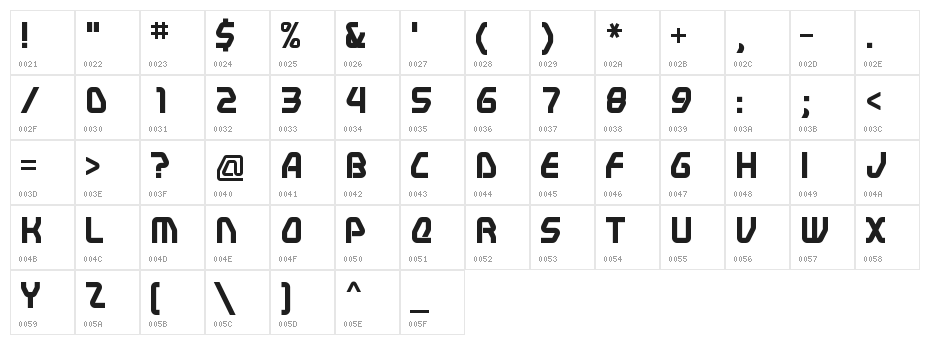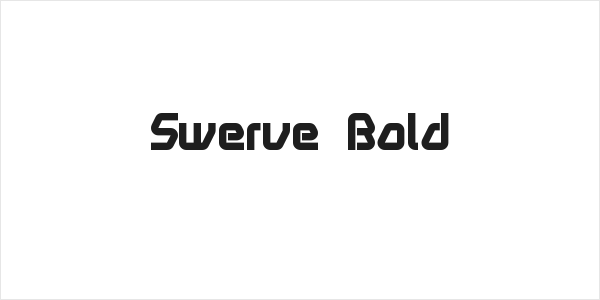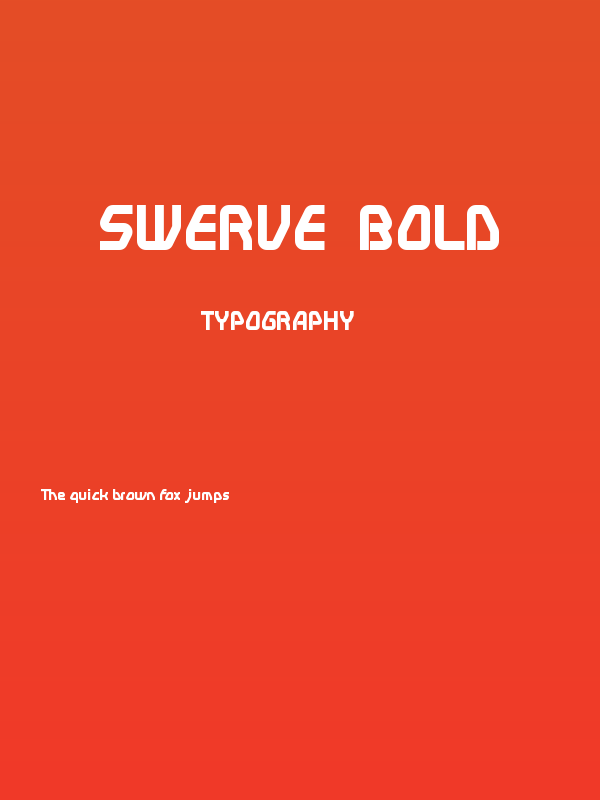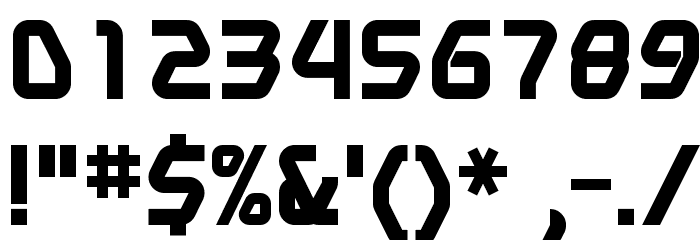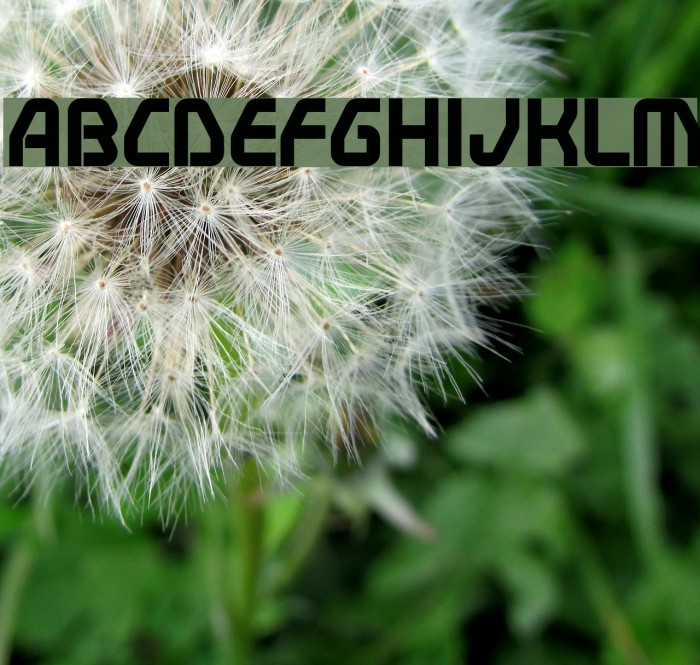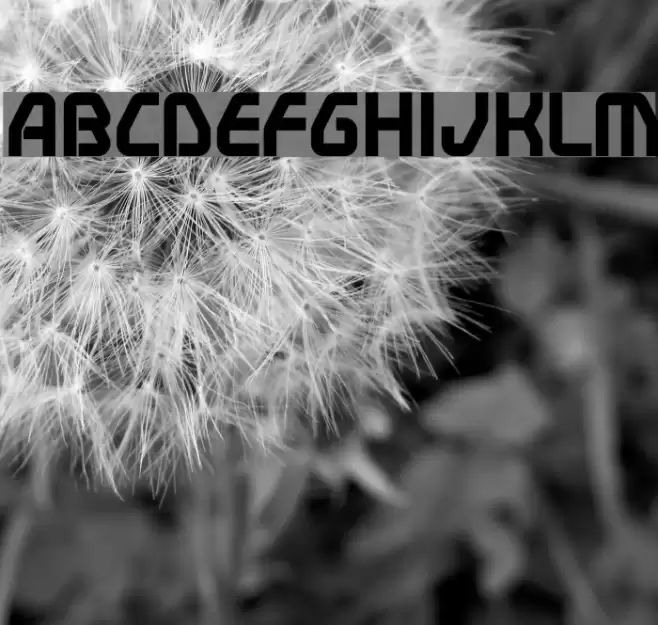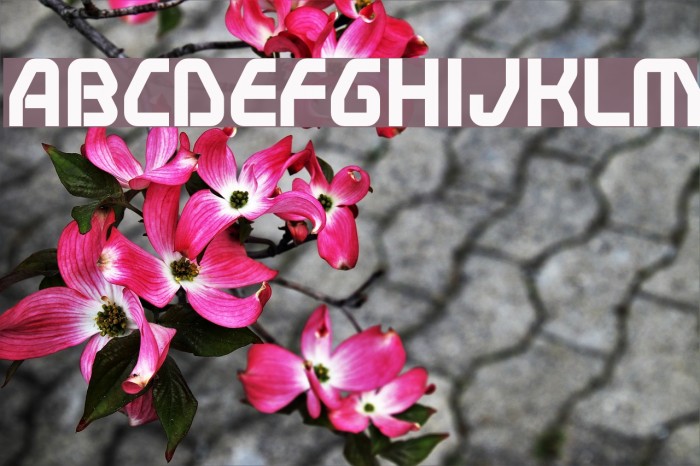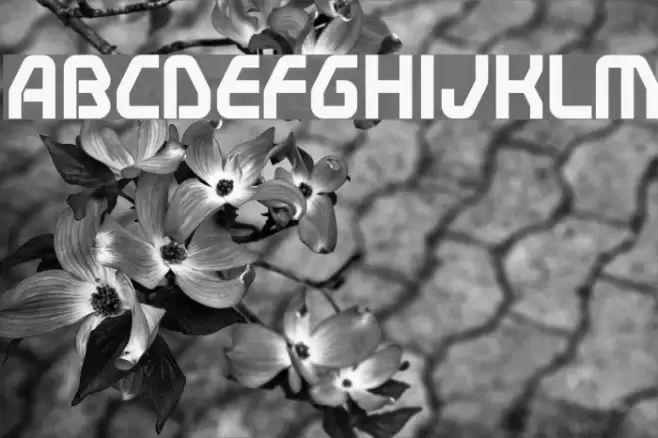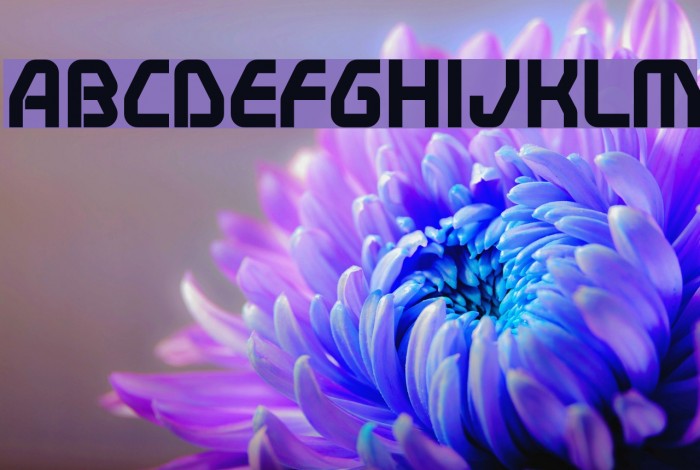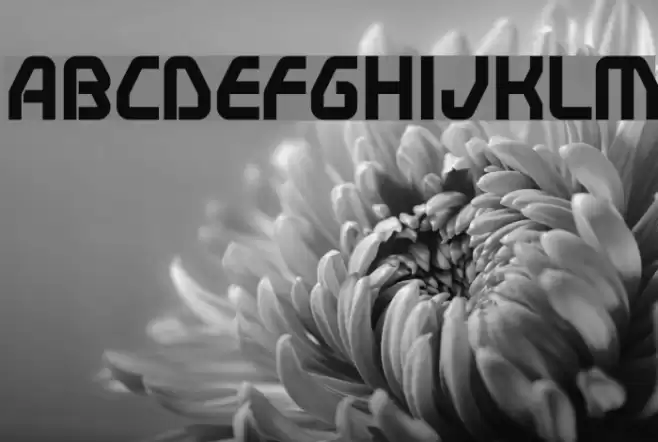
Swerve Bold Font
| Vorgeschlagene Projekte | Ideal for use in technology branding, sci-fi themed projects, video game titles, and modern advertising campaigns. |